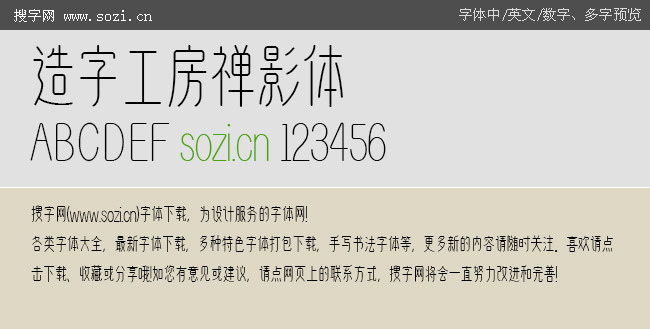
造字工房禪影體
搜字網(wǎng)給大家提供一款造字工房禪影體中文字體下載,造字工房禪影體筆觸較為纖細(xì),字體清晰且大氣,字體外觀細(xì)長,適合應(yīng)用于藝術(shù)設(shè)計、平面宣傳設(shè)計、網(wǎng)頁設(shè)計等應(yīng)用。(本字體為個人非商用版,如需要商用請聯(lián)系官方購買版權(quán))